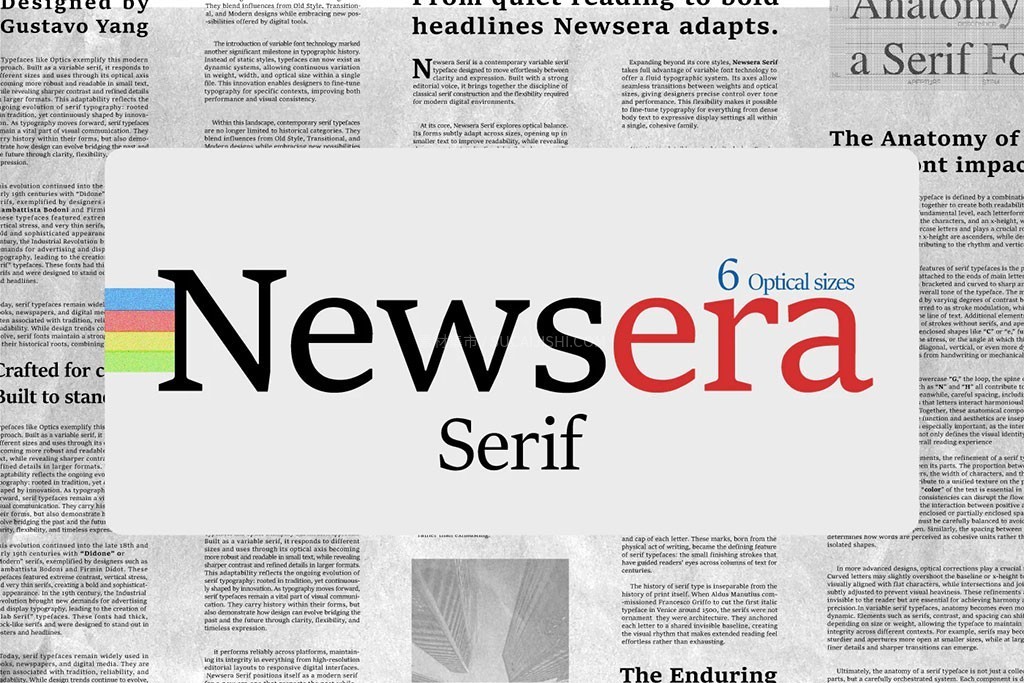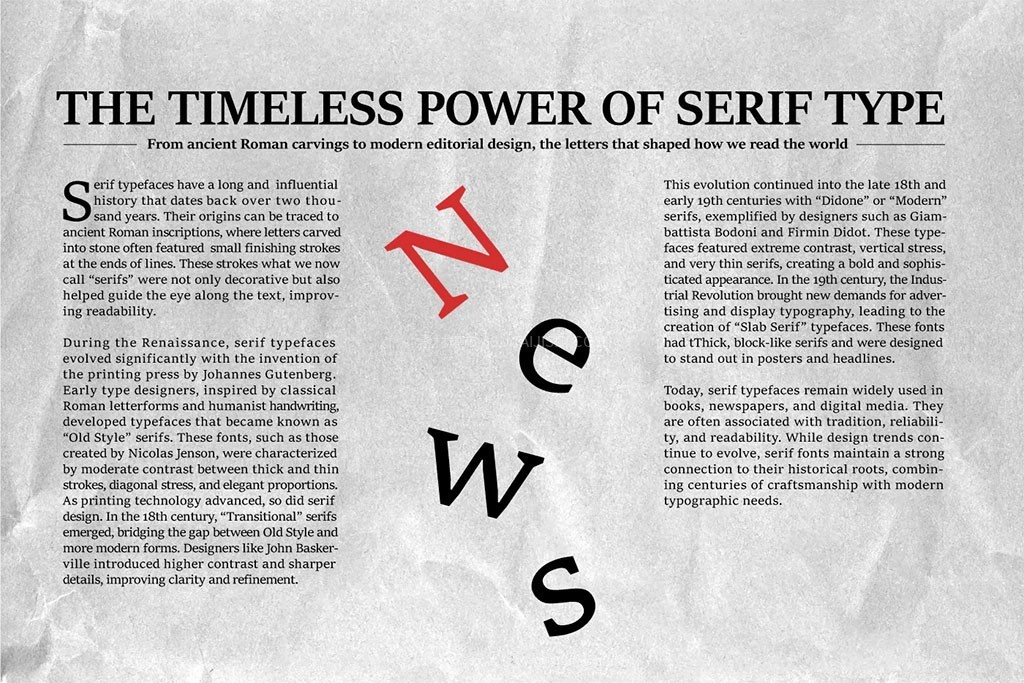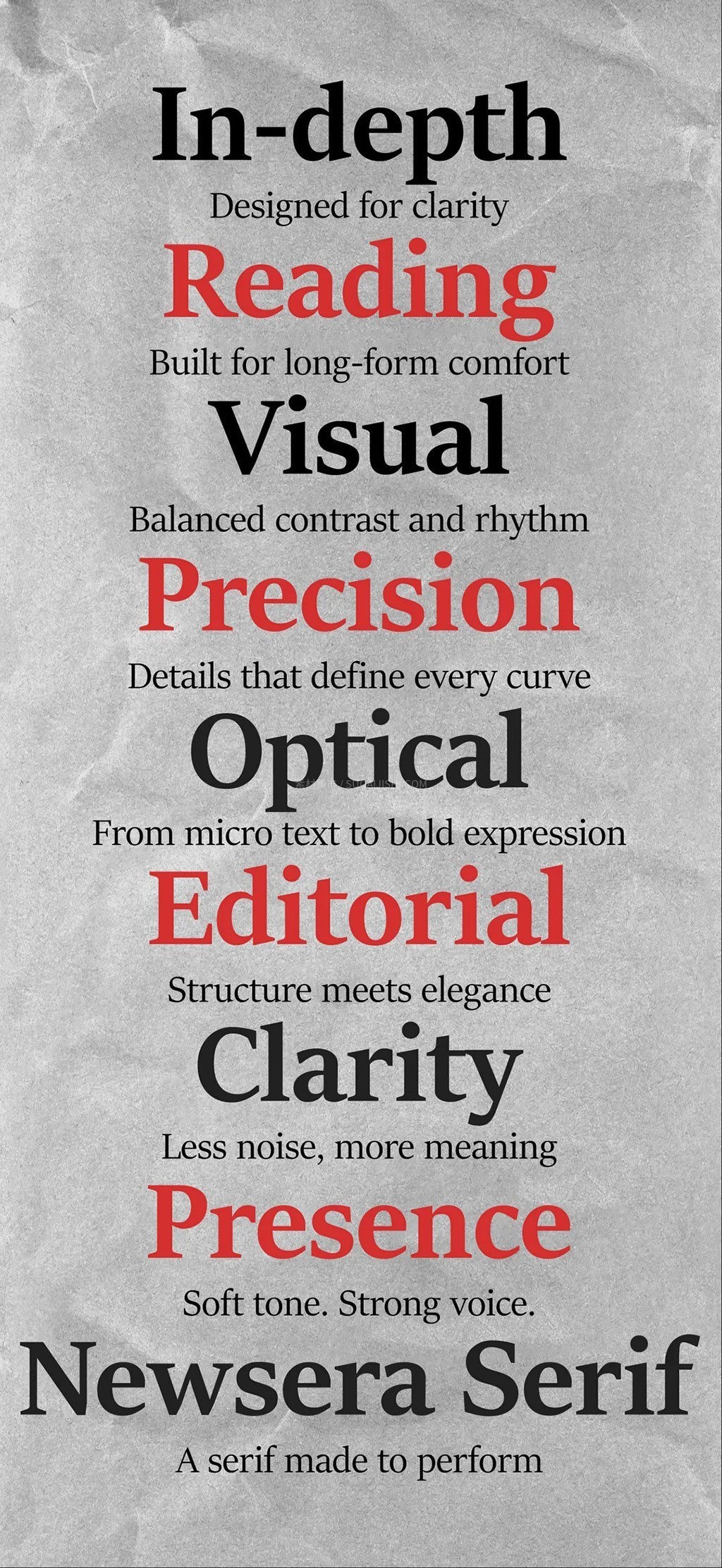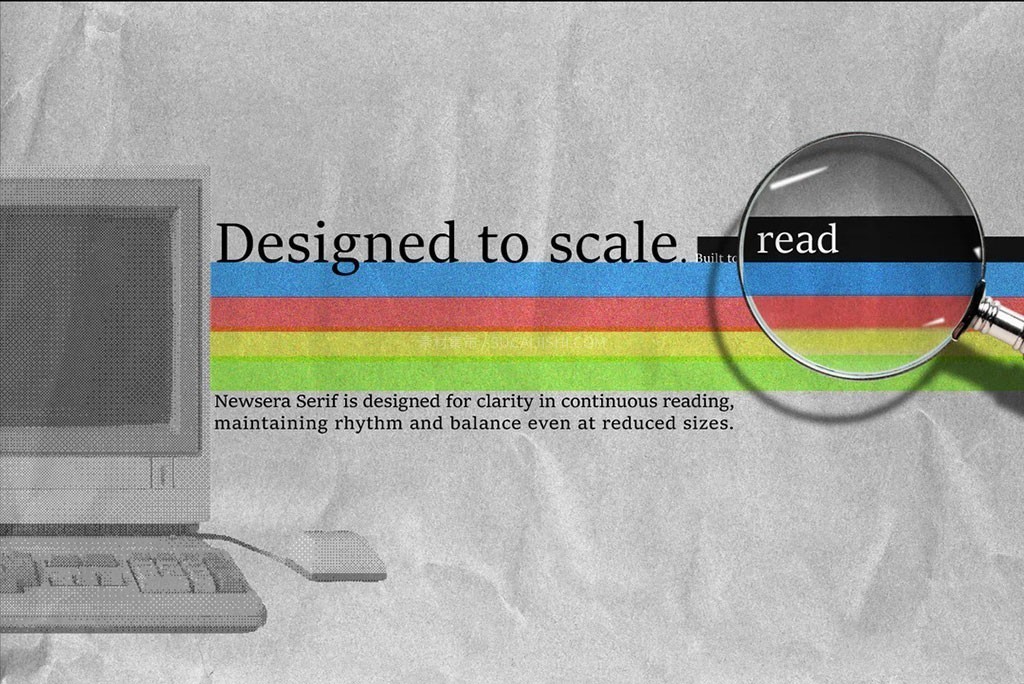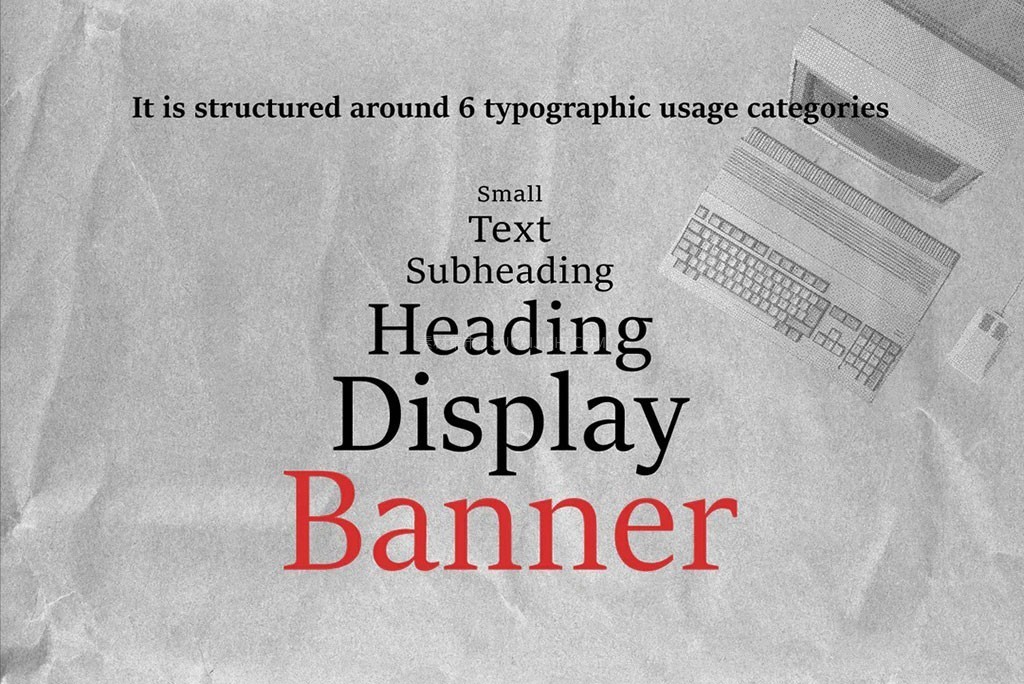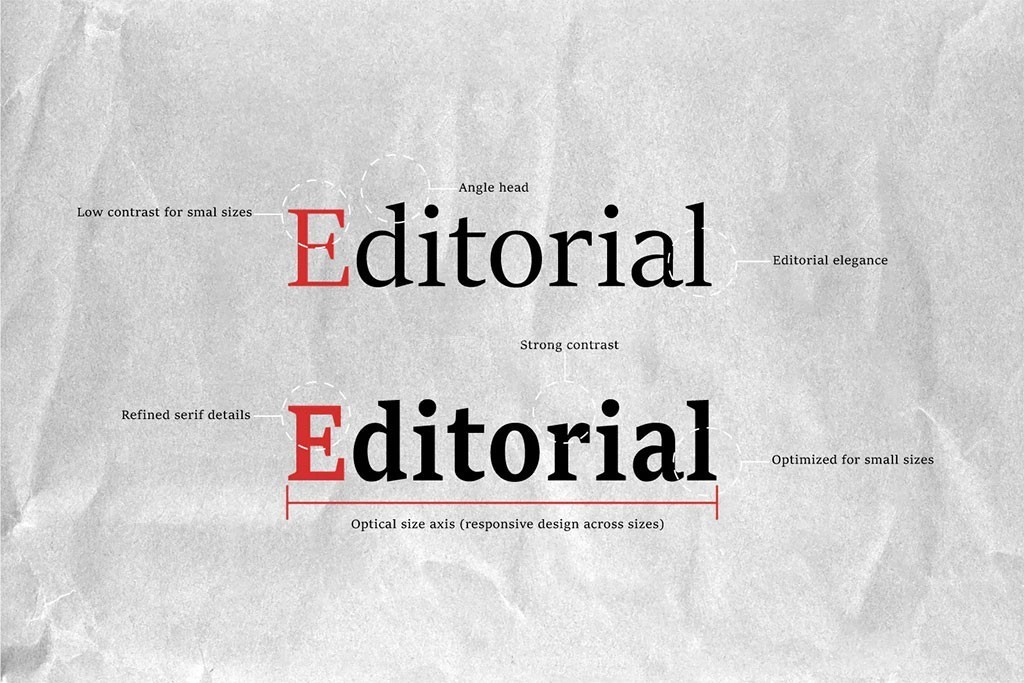
Newsera英文报纸衬线字体(支持桌面端商用)
一款极其百搭的宝藏衬线字体——Newsera Serif!由设计师杨古斯塔沃精心打造,它把传统排版的优雅感和现代实用的清晰度平衡得刚刚好。这款字体在经典衬线字体的骨架上,加入了非常有呼吸感的粗细对比和流畅的笔画节奏。这不仅让它在长篇阅读时超级舒适、不费眼,还自带一种高级的现代调调!最关键的是,它支持个人及桌面端的免费商业使用哦。不管你是用来排版长篇文案,还是做吸睛的品牌Logo、大标题,它的表现都相当稳,绝对是字库里的必备款。